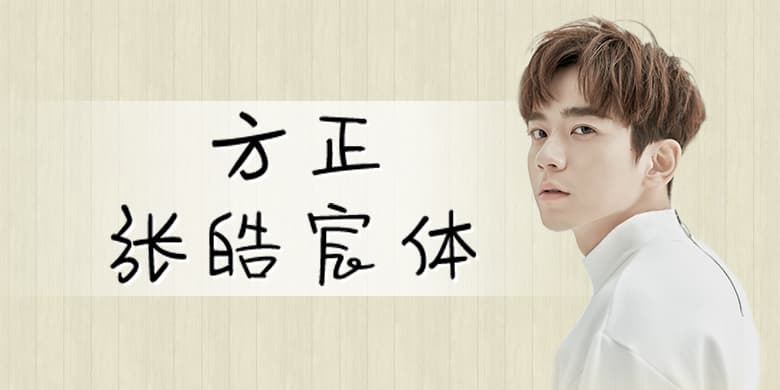
品牌:方正手迹设计师:张皓宸发行时间:2019字库编码:大陆简体(GB2312-80)分类:常规书写·硬笔字体属性:精品字
张皓宸,中国新生代作家、编剧、插画师。该字体有行书意味,但有别于传统行书,部件完全重新设计,使其更加具有浓浓的暖男气息。适用于现代诗歌、短文的排版以及文化、商业类品牌的广告语设计。